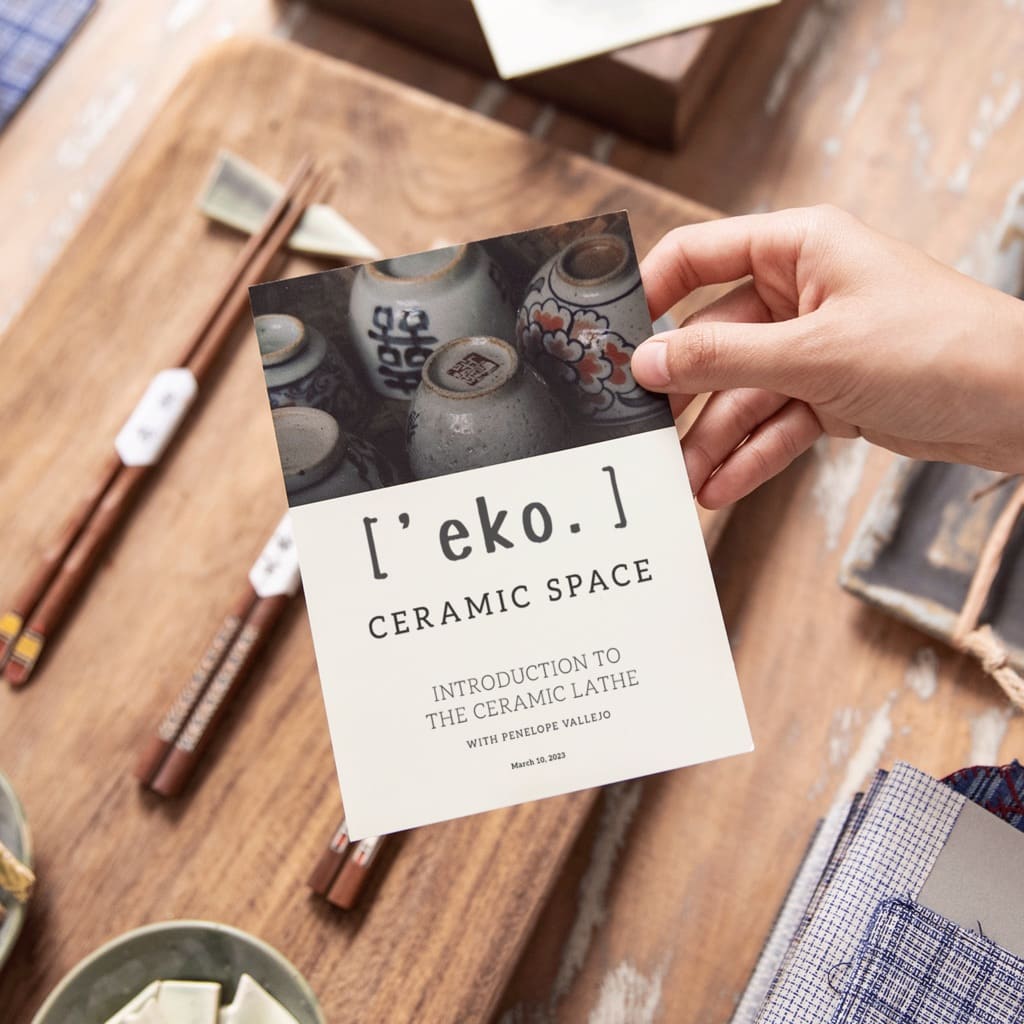
Lesefreundliche Schriftarten stellen sicher, dass Ihre Botschaft einfach aufgenommen und sofort verstanden wird.
Die von Ihnen gewählten Schriften sind ein wesentlicher Bestandteil Ihres Webdesigns und vermitteln Interessenten sowie potenzieller Kundschaft schnell Ihre Markenidentität. Sie sollten daher gut lesbare Schriftarten wählen, schließlich wirken sie sich auf alles aus: wie Ihre Marke wahrgenommen wird und wie zugänglich Ihre Inhalte über Print- und digitale Kanäle hinweg erscheinen.
Angesichts der großen Masse verfügbarer Schriftarten kann die Auswahl jedoch überwältigend erscheinen. Wir zeigen auf, was eine Schriftart gut lesbar macht, und stellen Ihnen zwölf Schriftarten vor, die Sie für alles verwenden können, von der Website für Ihr Kleinunternehmen bis hin zu gedruckten Marketingmaterialien. Sie erfahren, wie Sie serifenbetonte und serifenlose Schriften miteinander vergleichen, lernen die Basics zu Schriftlizenzen kennen und erfahren, wie Sie die besten Schriftkombinationen für Ihre Marke auswählen.
- Für effektives Branding und Design benötigen Sie gut lesbare Schriftarten – so vermitteln Sie Ihre Botschaft klar, barrierefrei und ansprechend für alle Zielgruppen.
- Damit Schriften sowohl in digitaler als auch gedruckter Form leserlich erscheinen, müssen Sie auf deutliche Formen, ausgewogene Abstände und einfach unterscheidbare Buchstaben achten.
- Zu den Schriftarten mit der besten Lesbarkeit gehören Georgia, Helvetica, Roboto und Verdana. Sie bieten zudem eine große Vielseitigkeit für den geschäftlichen Einsatz.
- Die Lesbarkeit hängt vom Einsatzort der Schrift ab: Sans-Serif-Schriften ohne Serifen eignen sich besonders für Bildschirme, während einfache serifenbetonte Schriftarten gedruckten Materialien Wärme, Autorität und eine raffiniertere Anmutung verleihen.
Welche Eigenschaften verbessern die Lesbarkeit einer Schriftart?
Ob Sie nach Schriftarten für Flyer und Falzflyer oder geeigneten Fonts für Social Media und Ihre Websites suchen, gut lesbare Schriftarten haben einige wichtige Merkmale gemeinsam, die sie deutlicher und zugänglicher machen. Dies sind einige Merkmale lesefreundlicher Typografie:
- Mittellänge: Dies ist die relative Höhe von Kleinbuchstaben im Vergleich zu Großbuchstaben. Höhere Kleinbuchstaben (wie das x) verbessern die Lesbarkeit auf Bildschirmen, während sie im Druck das Lesen längerer Texte erleichtern.
- Strichkontrast: Dies ist die Varianz zwischen dicken und dünnen Linien. Schriftarten mit geringem Kontrast lassen sich auf Bildschirmen besser lesen. Im Druck können Schriftarten mit höherem Kontrast großartig aussehen, ohne an Klarheit zu verlieren.
- Spationierung sowie Unterschneidung (Kerning): Damit ist der Abstand zwischen einzelnen Buchstaben gemeint. Ein ausgewogener Abstand verhindert, dass der Text gedrängt aussieht, und macht es einfacher, Bildschirmtexte zu überfliegen und zu erfassen. Durchdachte Zeichenabstände verbessern auch die Lesbarkeit im Druck, insbesondere bei Absätzen mit hoher Wortdichte.
- Unterscheidbarkeit: Gut lesbare Schriftarten weisen klare Unterschiede zwischen den Buchstaben auf (wie i, j, 1 und l). Damit werden Verwechslungen bei digitalen Texten vermieden und die Genauigkeit bei gedruckten Schildern oder Fließtexten verbessert.
- Serifenbetonte oder serifenlose Schriften: Serifenschriften wirken aufgrund ihrer kleinen dekorativen Striche etwas traditioneller und eignen sich besonders für Fließtext. Serifenlose Schriften wirken einfach und schnörkellos, was sie zur besseren Wahl für Webdesign und mobile Inhalte macht. Serifenlose Schriften lassen sich auf digitalen Geräten leichter lesen; einfache Schriften mit Serifen bieten sich hingegen für gedruckte Marketingmaterialien an.
Schriften mit oder ohne Serifen: Welche sind besser lesbar?
In der Debatte um serifenbetonte und serifenlose Schriften gibt es keinen eindeutigen Gewinner. Die beste Schriftart in puncto Lesbarkeit hängt von Zweck, Format und Zielgruppe des Textes ab. Serifenschriften wie Georgia haben kleine dekorative Horizontalstriche an den Enden der Buchstabenlinien; bei serifenlosen Schriften wie Helvetica, Roboto und Verdana gibt es die als Serifen bezeichneten Striche nicht, wodurch das Erscheinungsbild etwas deutlicher und minimalistischer wirkt.
Verwenden Sie eine serifenlose Schrift, wenn Sie Text benötigen, der auf einen Blick überfliegbar sein soll. Das gilt besonders für Websites, kleine Bildschirme, Apps, Social-Media-Grafiken, Werbetechnik, Navigationsmenüs, Handlungsaufforderungen (CTAs), Produktetiketten und prägnantes Messaging im digitalen Raum.
Verwenden Sie eine Serifenschrift, wenn Sie ein traditionelleres, eleganteres oder redaktionelles Gefühl vermitteln möchten. Das fällt hauptsächlich bei gedruckten Materialien wie Falzflyern, Postkarten, Menüs, Einladungen und längeren Fließtexten für Ihr Brand Storytelling ins Gewicht.
Verwenden Sie beide, wenn Sie Kontrast und Hierarchie schaffen möchten. Viele Marken verwenden eine Serifenschrift für Überschriften oder Premium-Branding und kombinieren diese mit einer serifenlosen Schrift für den Fließtext, Bildunterschriften und praktische Informationen.
Was sind die besten Schriftarten für Schilder?
Für Schilder bieten sich unter anderem Verdana, Helvetica und Futura an – besonders, wenn sie in augenfälligen, kontrastreichen Farben gedruckt werden.
Welche Schriftarten eignen sich am besten für Logos?
Bei Schriftarten für Logos ist wichtig, das sie markant, unverwechselbar und in verschiedenen Größen leicht lesbar sind. Serifenlose Schriftarten wie Helvetica und Futura eignen sich gut für moderne Marken; einfache Serifenschriften wie Georgia passen mit Ihrem vertrauenswürdigen Eindruck eher zu Traditionsunternehmen.